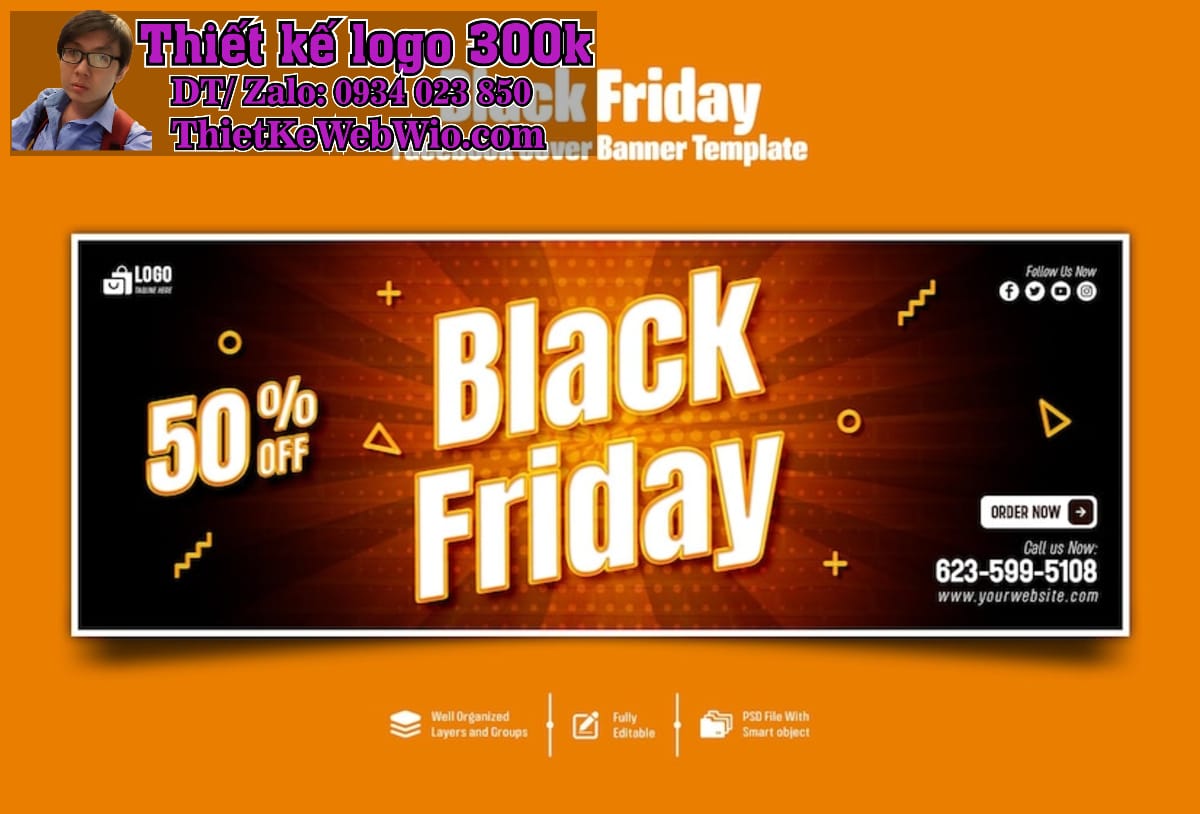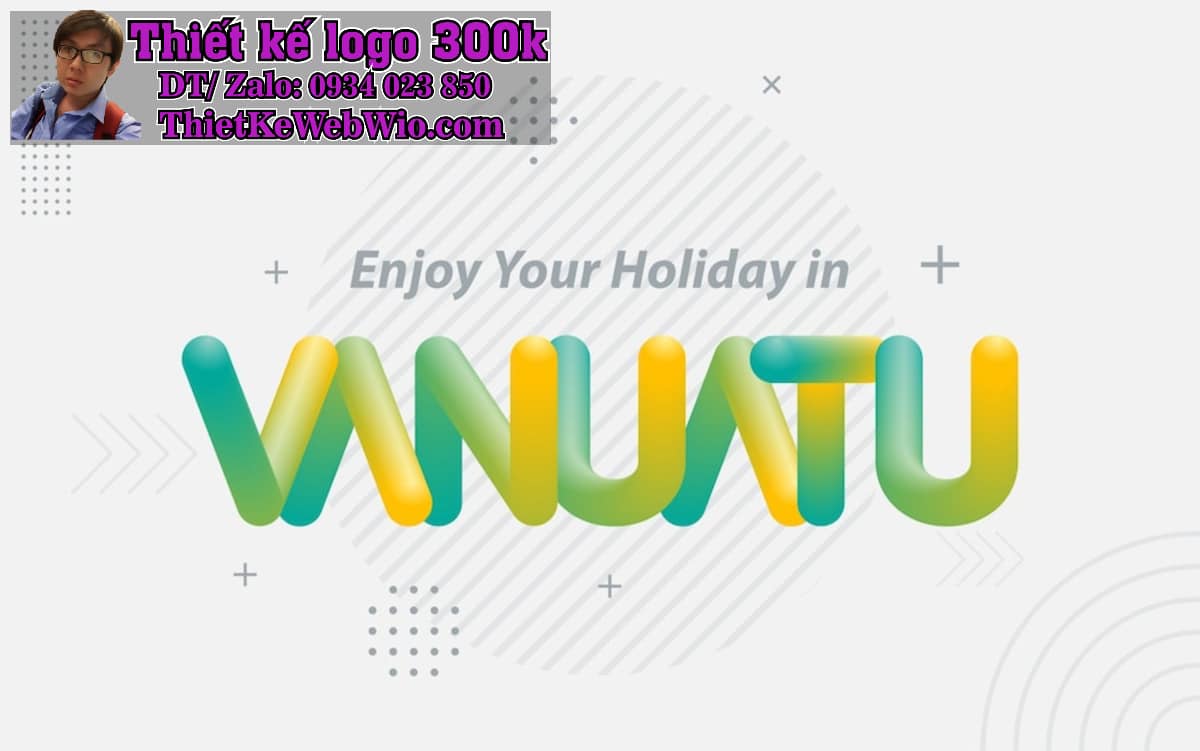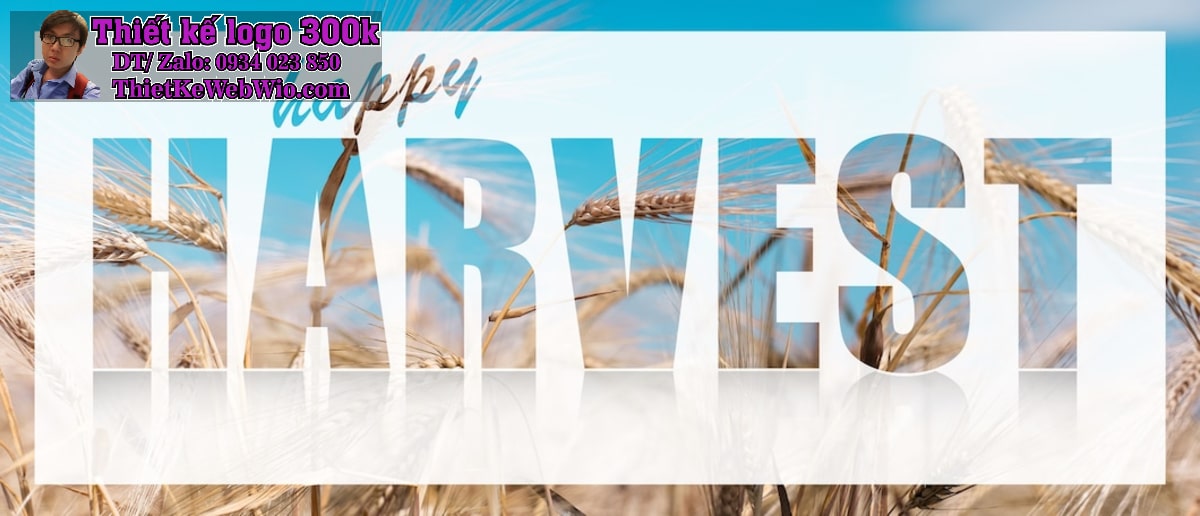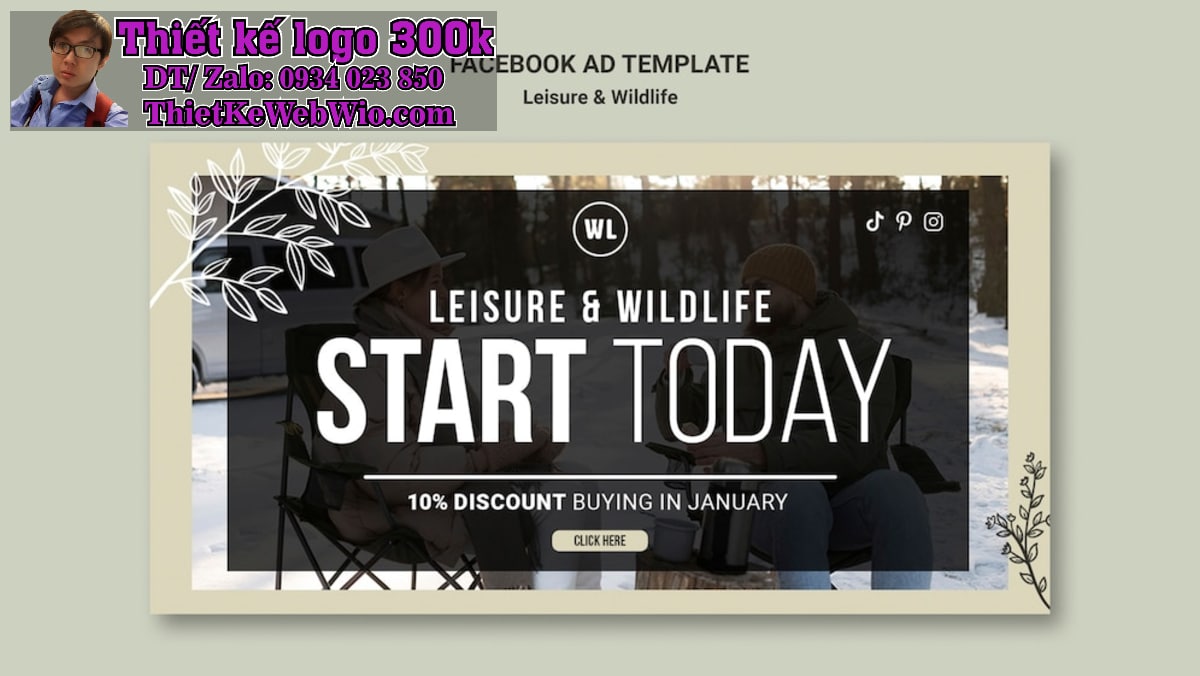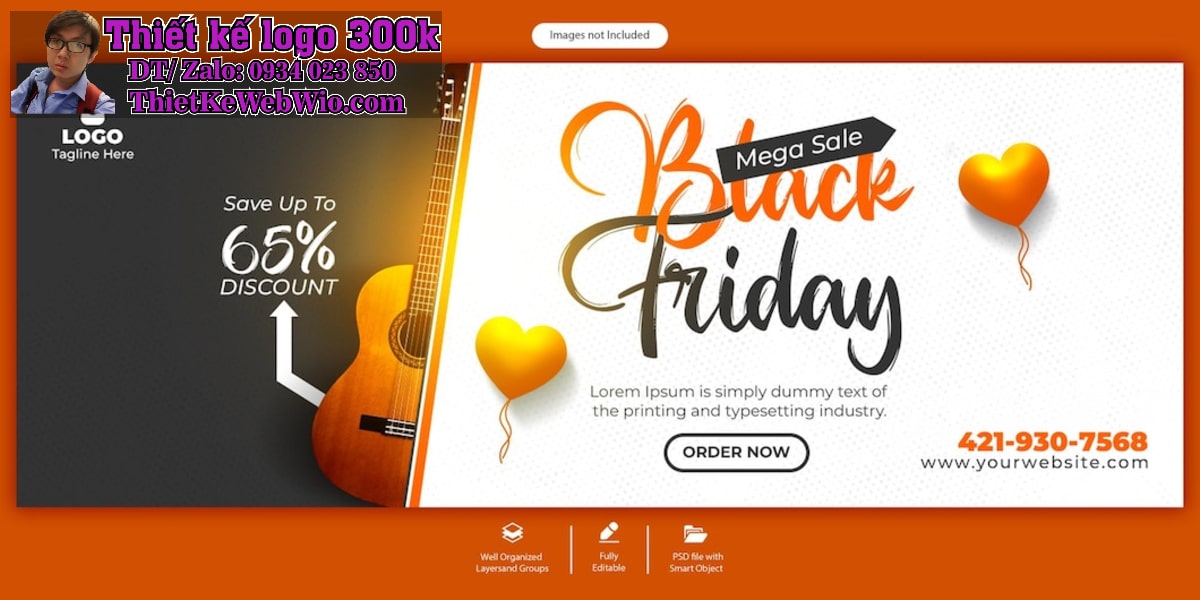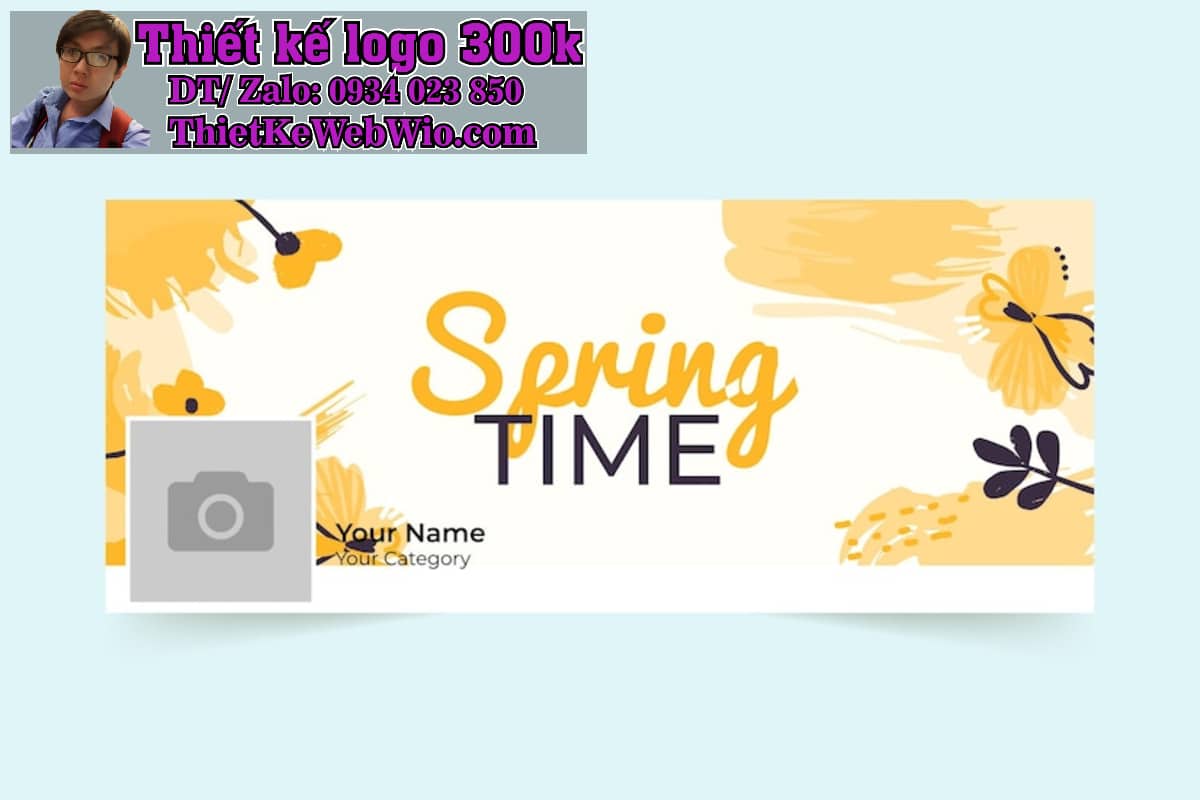
Trong Font Chữ Trong Thiết Kế Banner Ảnh Bìa Facebook, font chữ đóng vai trò quan trọng không kém gì hình ảnh hay màu sắc. Một font chữ phù hợp không chỉ giúp truyền tải thông điệp mà Font Chữ Trong Thiết Kế Banner Ảnh Bìa Facebook còn tạo nên ấn tượng mạnh mẽ với người xem. Bài viết này sẽ phân tích vai trò của font chữ, các loại font phổ biến, và những lưu ý khi lựa chọn Font Chữ Trong Thiết Kế Banner Ảnh Bìa Facebook.
1. Vai Trò Của Font Chữ Trong Thiết Kế Banner Ảnh Bìa Facebook
1.1. Truyền Tải Thông Điệp trong Font Chữ Trong Thiết Kế Banner Ảnh Bìa Facebook
Font chữ là công cụ chính để truyền tải thông điệp của bạn đến người xem. Một thiết kế banner dù đẹp đến đâu mà thông điệp không rõ ràng sẽ không mang lại hiệu quả. Font chữ cần phải dễ đọc và phù hợp với nội dung của banner.
1.2. Khẳng Định Thương Hiệu Font Chữ Trong Thiết Kế Banner Ảnh Bìa Facebook
Font chữ cũng là một phần của nhận diện thương hiệu. Các thương hiệu lớn thường có những font chữ riêng biệt mà khách hàng dễ dàng nhận diện. Việc sử dụng font chữ nhất quán trong tất cả các banner và tài liệu marketing sẽ giúp củng cố thương hiệu.
1.3. Gợi Cảm Xúc
Font chữ không chỉ đơn thuần là hình thức mà còn có thể gợi lên những cảm xúc nhất định. Ví dụ, font chữ viết tay có thể mang lại cảm giác gần gũi, trong khi font chữ sans-serif thường gợi lên sự hiện đại và chuyên nghiệp.
2. Các Loại Font Chữ Phổ Biến Trong Font Chữ Trong Thiết Kế Banner Ảnh Bìa Facebook
2.1. Font Serif
Font serif, với các nét chân ở đầu mỗi ký tự, thường được xem là cổ điển và trang trọng. Chúng thường được sử dụng trong các banner mang tính chất nghiêm túc, như quảng cáo cho các sự kiện văn hóa hoặc các tổ chức giáo dục. Ví dụ: Times New Roman, Georgia.
2.2. Font Sans-serif
Font sans-serif không có các nét chân, mang lại cảm giác hiện đại và sạch sẽ. Đây là loại font phổ biến nhất trong thiết kế banner hiện đại, đặc biệt là cho các thương hiệu trẻ trung và năng động. Ví dụ: Arial, Helvetica, Roboto.
2.3. Font Viết Tay
Font viết tay mang lại cảm giác cá nhân và thân thiện. Chúng thường được sử dụng cho các banner quảng bá sản phẩm handmade, quán cà phê hoặc các sự kiện cá nhân như đám cưới. Ví dụ: Pacifico, Dancing Script.
2.4. Font Đồ Họa
Font đồ họa là những kiểu chữ sáng tạo và độc đáo, thường được sử dụng để tạo điểm nhấn cho các banner. Tuy nhiên, cần lưu ý rằng font này thường khó đọc nếu không được sử dụng một cách hợp lý.
3. Lựa Chọn Font Chữ Phù Hợp Cho Font Chữ Trong Thiết Kế Banner Ảnh Bìa Facebook
3.1. Độ Dễ Đọc với Font Chữ Trong Thiết Kế Banner Ảnh Bìa Facebook
Độ dễ đọc là yếu tố quan trọng nhất khi chọn font chữ cho banner. Tránh sử dụng những font chữ quá cầu kỳ hoặc có nhiều chi tiết nhỏ, vì chúng có thể khiến người xem khó khăn khi đọc thông điệp. Hãy chọn những font chữ đơn giản và rõ ràng.
3.2. Kích Thước Chữ của Font Chữ Trong Thiết Kế Banner Ảnh Bìa Facebook
Kích thước chữ cũng rất quan trọng. Đảm bảo rằng chữ đủ lớn để có thể đọc được ngay cả khi người xem chỉ lướt qua. Nên sử dụng kích thước chữ lớn cho tiêu đề và nhỏ hơn cho các thông tin bổ sung.
3.3. Màu Sắc Font Chữ Trong Thiết Kế Banner Ảnh Bìa Facebook
Màu sắc của font chữ cần phải tương phản với nền để dễ đọc. Nếu nền tối, hãy sử dụng màu sáng cho chữ và ngược lại. Sự kết hợp màu sắc hài hòa sẽ giúp banner trở nên bắt mắt hơn.
3.4. Số Lượng Font Chữ Trong Thiết Kế Banner Ảnh Bìa Facebook
Sử dụng quá nhiều loại font chữ trong một banner có thể làm rối mắt người xem. Tốt nhất chỉ nên sử dụng từ 1 đến 2 loại font cho mỗi banner. Ví dụ, bạn có thể sử dụng một font cho tiêu đề và một font khác cho phần mô tả.
4. Ứng Dụng Font Chữ Trong Các Thể Loại Font Chữ Trong Thiết Kế Banner Ảnh Bìa Facebook
4.1. Font Chữ Trong Thiết Kế Banner Ảnh Bìa Facebook Quảng Cáo Sản Phẩm
Khi thiết kế banner quảng cáo sản phẩm, hãy chọn font chữ dễ đọc, sắc nét để làm nổi bật thông điệp chính. Font sans-serif thường là lựa chọn tốt nhất cho loại banner này.
4.2. Font Chữ Trong Thiết Kế Banner Ảnh Bìa Facebook Sự Kiện
Đối với banner sự kiện, bạn có thể chọn font chữ viết tay để tạo không khí gần gũi và thân thiện. Đảm bảo rằng thông tin về thời gian, địa điểm và cách thức tham gia được trình bày rõ ràng.
4.3. Font Chữ Trong Thiết Kế Banner Ảnh Bìa Facebook Thông Báo Khuyến Mãi
Font chữ lớn, nổi bật sẽ thu hút sự chú ý của người xem đến các chương trình khuyến mãi. Sử dụng màu sắc nổi bật để nhấn mạnh thông điệp.
5. Một Số Lưu Ý Khi Sử Dụng Font Chữ Trong Thiết Kế Banner Ảnh Bìa Facebook
5.1. Thử Nghiệm Font Chữ Trong Thiết Kế Banner Ảnh Bìa Facebook
Đừng ngần ngại thử nghiệm với các loại font khác nhau để tìm ra sự kết hợp hoàn hảo nhất cho banner của bạn. Sử dụng các công cụ thiết kế như Canva hoặc Adobe Illustrator để dễ dàng thử nghiệm.
5.2. Đảm Bảo Tính Nhất Quán của Font Chữ Trong Thiết Kế Banner Ảnh Bìa Facebook
Hãy đảm bảo rằng font chữ bạn chọn được sử dụng nhất quán trong tất cả các banner và tài liệu marketing khác. Điều này giúp tạo ra một hình ảnh thương hiệu đồng nhất và chuyên nghiệp.
6. Kết Luận Font Chữ Trong Thiết Kế Banner Ảnh Bìa Facebook
Font Chữ Trong Thiết Kế Banner Ảnh Bìa Facebook là một phần không thể thiếu trong thiết kế banner ảnh bìa Facebook. Việc lựa chọn font chữ phù hợp không chỉ giúp truyền tải thông điệp một cách hiệu quả mà Font Chữ Trong Thiết Kế Banner Ảnh Bìa Facebook còn khẳng định được bản sắc thương hiệu. Hãy cân nhắc kỹ lưỡng các yếu tố như độ dễ đọc, màu sắc, và tính nhất quán để tạo ra những Font Chữ Trong Thiết Kế Banner Ảnh Bìa Facebook ấn tượng, thu hút sự chú ý của người xem và góp phần vào thành công của chiến dịch marketing của bạn.